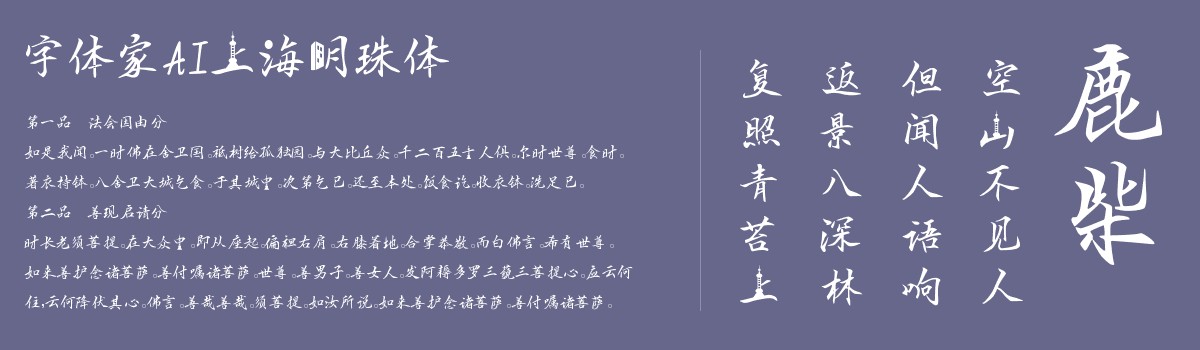
字体家AI上海明珠体
字体家AI上海明珠体是一款充满艺术感的字体,宛如指尖轻引的丝线。每个笔画的变化都像演奏乐章,从温柔的起笔到顺势的舒展,既有节奏感,又有韵律感。它稳重中透出轻盈,仿佛能感受到笔尖的起伏。更特别的是,这款字体融合了上海明珠塔和高楼大厦的元素,使其既时尚又美观。
在欣赏这款字体时,我觉得它仿佛是一座隐形的桥梁,连接着传统书法的温润底蕴和现代设计的流畅生机。无论是用于广告标题、海报文案,还是网页广告,它都能为您的作品增添无与伦比的视觉魅力。字体家AI上海明珠体,真的是设计师们的绝佳选择!